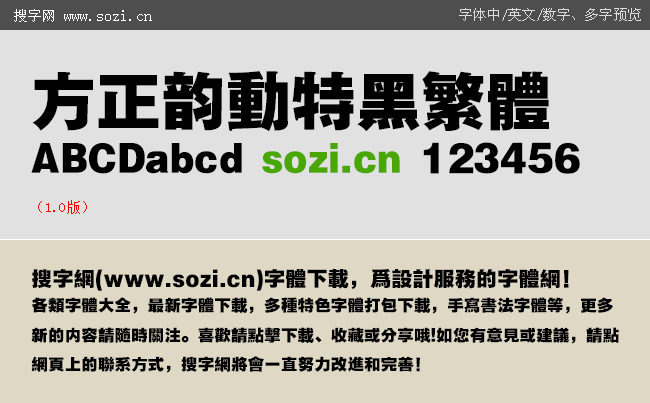
方正韵动特黑繁体(FZYDTHFW)
搜字网提供一款方正韵动特黑繁体中文字体下载,韵动黑去掉了原黑体笔画上的喇叭口装饰,使字体风格更加简约时尚。在竖、撇、提的起笔处增加了装饰头,使字体更具个性。在撇、捺、点的设计上力求角度自然合理,不仅舒展有度,而且富有弹性和力度;竖钩的长短适度,转折灵活。对字面适当加以扩大,使字体更加庄重平稳,增强了版面的视觉冲击力。适合书籍设计、展板设计、海报设计等广告设计场合使用。